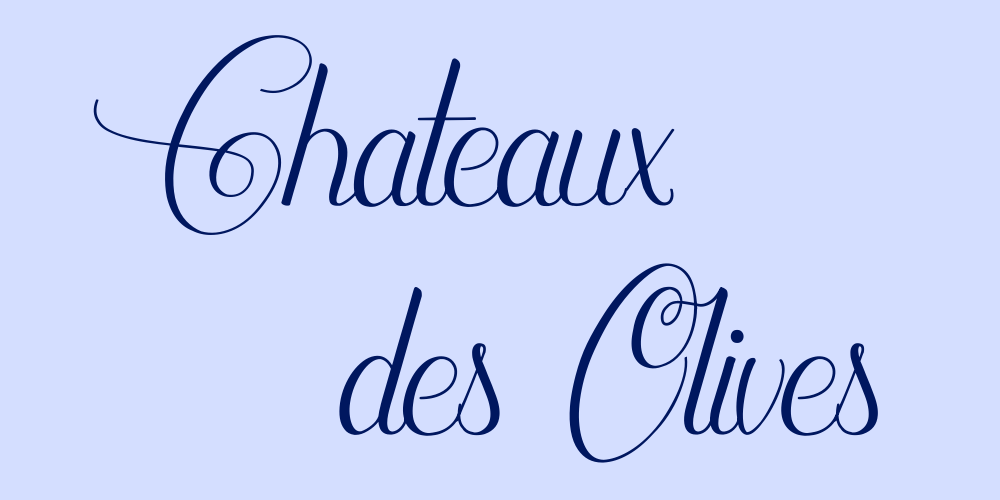
A Chateaux des Olives é uma fonte chamativa perfeita para aqueles que buscam estilo e elegância na tipografia. Desenhada pelo talentoso Hamilton, essa fonte possui linhas levemente onduladas que trazem uma sensação de tranquilidade e calma a qualquer projeto. Ideal para letras grandes em posters ou materiais publicitários, essa fonte também se destaca como uma ótima escolha para criações de arte livre e desenhos artísticos. Com seu design cuidadosamente elaborado, a Chateaux des Olives não apenas adicionará um toque sofisticado ao seu trabalho, mas também permitirá que você expressa sua personalidade através da escrita. Além disso, a fonte tem uma característica distintiva de linhas onduladas em forma de oliveira, oferecendo aos designers e criadores de conteúdo um elemento visual único para destacar seus trabalhos. Seja você um designer gráfico profissional ou apenas iniciante, a Chateaux des Olives é uma fonte que merece sua atenção. Compreendendo bem o valor da simplicidade e elegância, Hamilton desenvolveu essa fonte com precisão, oferecendo aos designers uma ferramenta poderosa para expressar seu trabalho de maneira única e profissional.